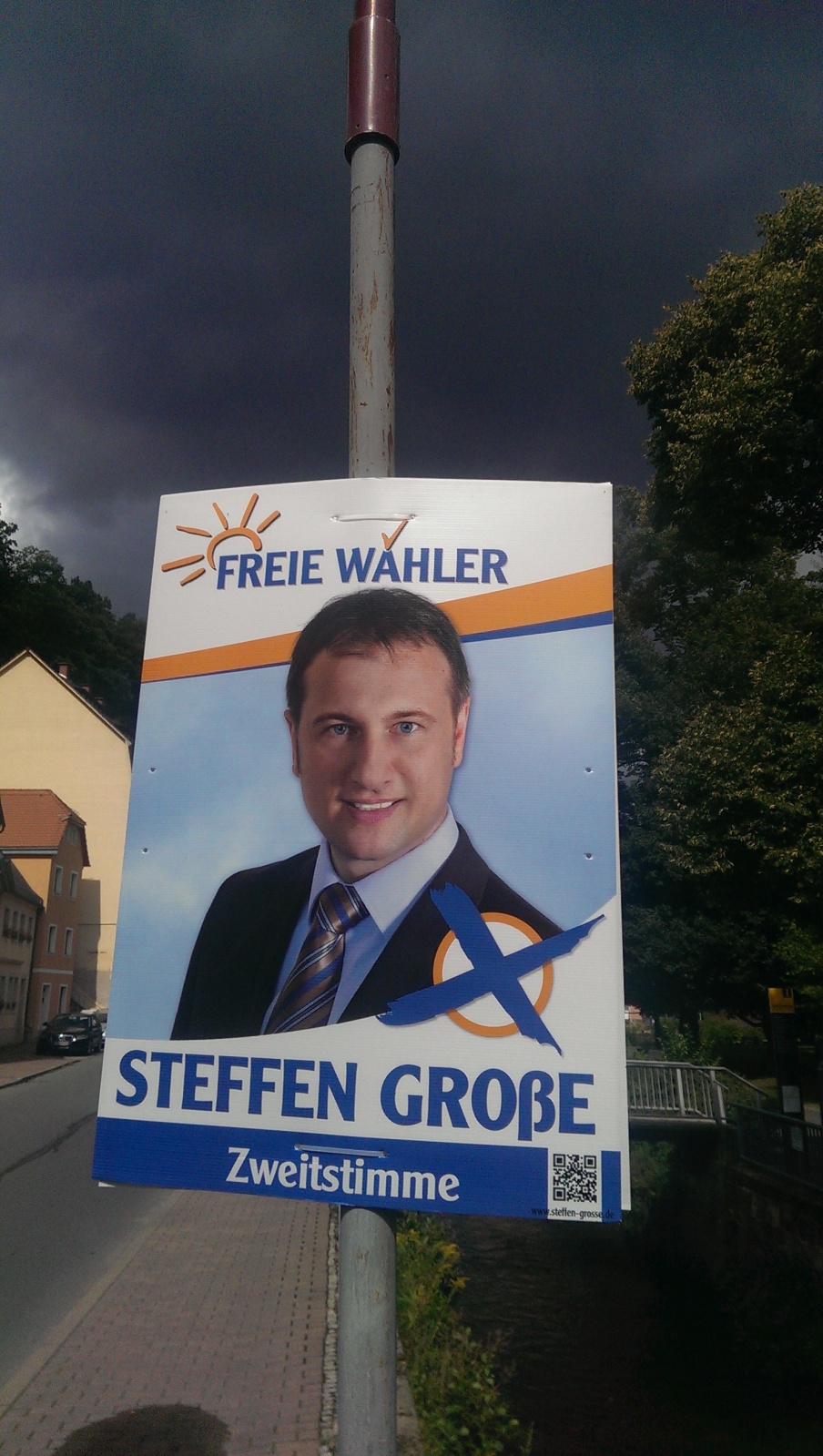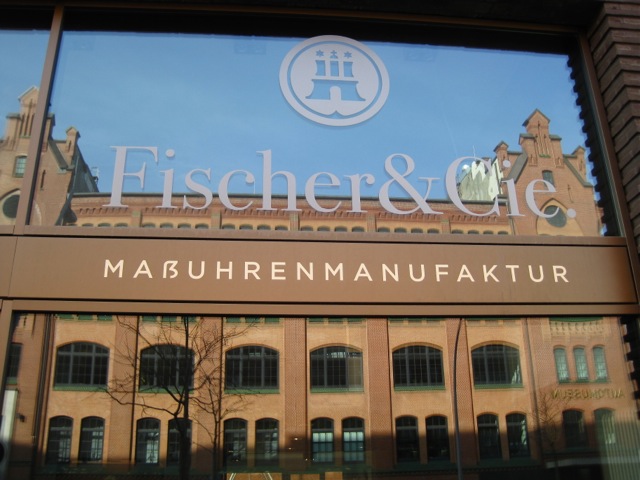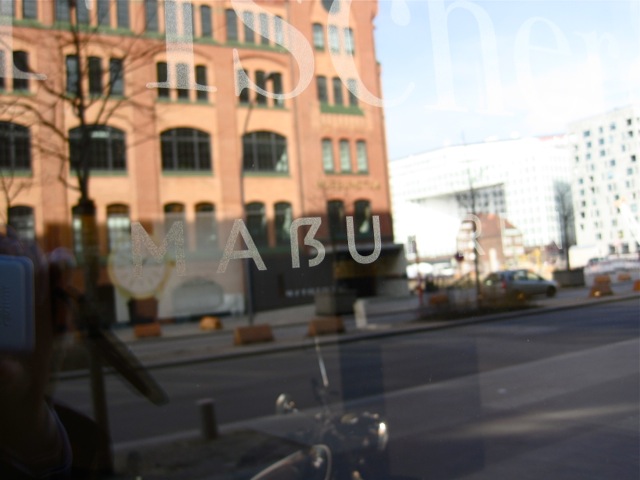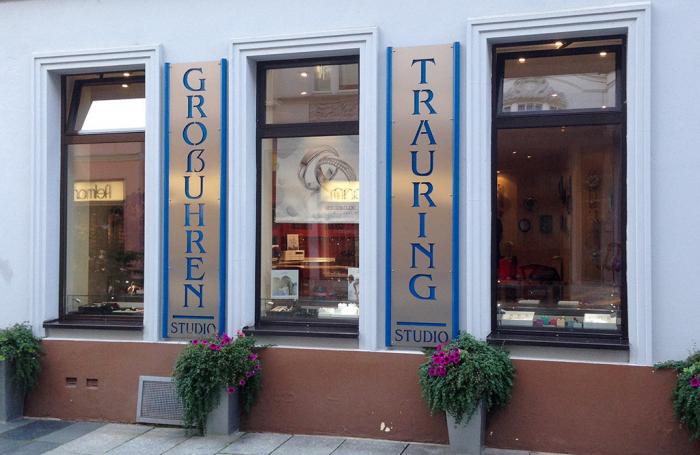
Da fällt mir ein: Diesen hier hatten Tobi und ich in der Hafencity fotografiert. Uhrenmenschen scheinen innovativ zu sein!
In diesem Fall ist es sicher besonders wünschenswert, jeden auch nur denkbaren Anklang an Mass(en)produkte zu vermeiden.
Nicht zu vergessen, dass niemand Massuren, ähm, Massagen erwartet.
Und genau deswegen würde auch der weiter oben verlinkte Vorschlag, Ş für das Versal-ß zu verwenden, nicht funktionieren. Woran würden Kunden bei MAŞUHREN denken? Klar, an Uhren irgendeines Ausländers namens »Maş«!